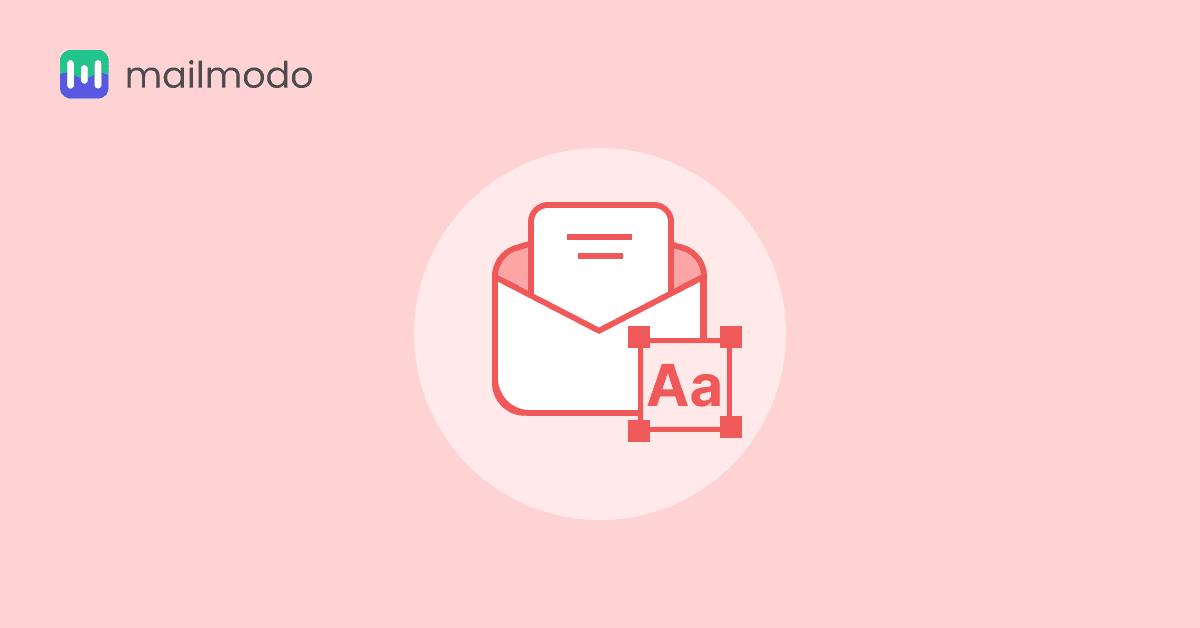
La tipografía juega un papel crucial en el éxito de tus campañas de email marketing. Una fuente bien elegida mejora la legibilidad, refuerza tu mensaje y crea una experiencia positiva para el usuario; mientras que una mala elección puede dificultar la lectura, generar confusión o incluso que tu email sea marcado como spam.
Tipos de Fuentes para Email: ¿Email-Safe vs Web-Safe?
No todas las fuentes se renderizan correctamente en todos los clientes de correo electrónico. Es fundamental comprender la diferencia entre fuentes email-safe y web-safe :
Fuentes Email-Safe
Estas fuentes están preinstaladas en la mayoría de los dispositivos y garantizan una visualización consistente en la gran mayoría de los clientes de correo electrónico, como Gmail, Outlook y Apple Mail. Ejemplos:
- Arial
- Times New Roman
- Georgia
- Verdana
- Courier New
- Lucida Sans
- Trebuchet MS
Fuentes Web-Safe
Estas fuentes están instaladas en la mayoría de los sistemas operativos, pero existe una mayor probabilidad de que no se rendericen correctamente si el dispositivo del receptor no las admite. Ejemplos:
- Helvetica
- Trebuchet MS
- Comic Sans MS
- Palatino Linotype
- Impact
- Lucida Console
- Lucida Grande
- Calibri
- Constantia
- Corbel
- Arial Narrow
- Terminal
- Century Gothic
- Papyrus
- Book Antiqua
- Cambria
- Candara
- Consolas
- Arial Black
- Arial MT Condensed Light
- Franklin Gothic Medium
- French Script MT
- Segoe UI
- Segoe Print
- Sylfaen
| Aspecto | Fuentes Email-Safe | Fuentes Web-Safe |
|---|---|---|
| Compatibilidad | Totalmente compatibles con la mayoría de los clientes de correo electrónico. | Principalmente compatibles con navegadores web, pero pueden no serlo con clientes de correo electrónico. |
| Uso | Ideales para email marketing y correos electrónicos transaccionales. | Mejores para sitios web o contenido online donde se requiere una visualización consistente en los navegadores. |
| Fuente de reserva | Incluyen una fuente de reserva para asegurar la legibilidad. | Pueden necesitar fuentes de reserva genéricas (p. ej., sans-serif o serif). |
| Personalización | Personalización limitada. | Mayor flexibilidad para los diseñadores. |
Recomendación: Prioriza las fuentes email-safe para asegurar la compatibilidad y la legibilidad en todos los clientes.
Cómo Elegir la Mejor Fuente para tu Email
La elección de la fuente debe considerar varios factores:
Considera el tono y la estructura de la fuente:
La psicología de las fuentes es importante. Una fuente moderna como Roboto o Verdana es adecuada para un público joven, mientras que una fuente serif como Times New Roman puede resultar más formal y profesional.
Tipos de familias de fuentes:
- Serif: Con serifas (pequeñas líneas al final de los trazos). Aspecto tradicional y formal (ej. Times New Roman, Georgia).
- Sans Serif: Sin serifas. Aspecto limpio y moderno (ej. Arial, Helvetica, Verdana).
- Decorativas: Estilos variados, alta expresividad, menor legibilidad (ej. Comic Sans, script).
Legibilidad y accesibilidad:
Prioriza la simplicidad y la claridad. Evita fuentes intrincadas que dificulten la lectura, especialmente para usuarios con discapacidades visuales. Fuentes como Arial y Verdana son excelentes opciones para la legibilidad.
Tamaño de la fuente:
Un tamaño de fuente demasiado pequeño dificulta la lectura, mientras que uno demasiado grande puede resultar abrumador. Se recomienda un tamaño de 14-16 px para el cuerpo del texto y 18-20 px para los encabezados.
7 Fuentes Recomendadas para Email Marketing
Analicemos algunas de las mejores opciones:
Arial:
Tipo: Sans serif. Tono: Moderno y legible. Uso: Cuerpo del texto.
Times New Roman:
Tipo: Serif. Tono: Formal y profesional. Uso: Cuerpo del texto o párrafos largos.
Georgia:
Tipo: Serif. Tono: Elegante y clásica. Uso: Newsletters y contenido extenso.
Helvetica:
Tipo: Sans serif. Tono: Neutro y moderno. Uso: Encabezados y elementos visuales.
Verdana:
Tipo: Sans serif. Tono: Amigable y simple. Uso: Encabezados, elementos visuales y contenido extenso.
Lucida Sans:
Tipo: Sans serif. Tono: Clara y amigable. Uso: Textos diversos, tablas, formularios.
Trebuchet MS:
Tipo: Sans serif. Tono: Moderno e informal. Uso: Textos del cuerpo, encabezados, subtítulos y CTA.
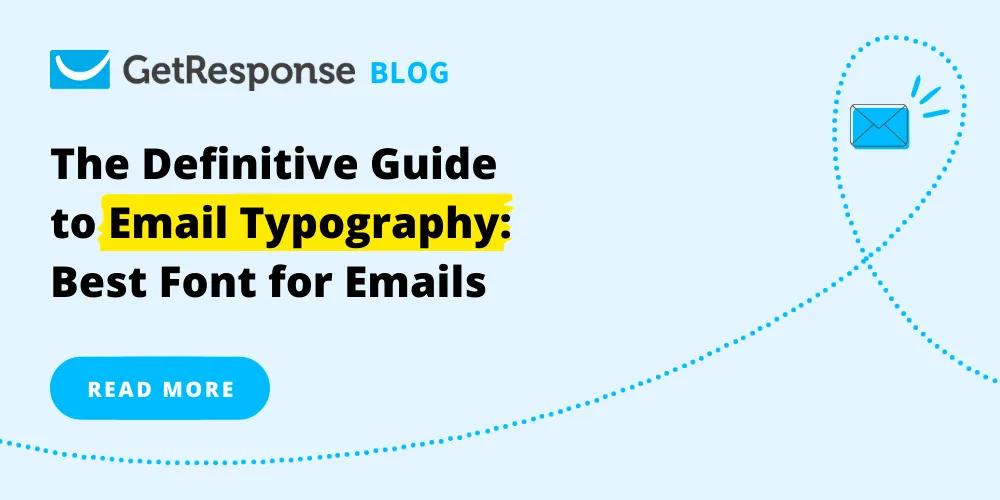
¿Qué pasa si mi fuente web-safe no se renderiza?
Aunque las fuentes web-safe están diseñadas para ser compatibles, siempre existe la posibilidad de que no se rendericen correctamente. En ese caso, la mayoría de las plataformas de correo electrónico utilizan una fuente de reserva para asegurar la legibilidad.
Uso de Fuentes Estéticas en Imágenes
Para usar fuentes más estéticas sin comprometer la compatibilidad, puedes incrustarlas en imágenes. Sin embargo, recuerda que el uso excesivo de imágenes puede aumentar el tamaño del correo electrónico y afectar su entrega.
Pruebas A/B para la Optimización
Realiza pruebas A/B con diferentes fuentes para determinar cuál funciona mejor para tu público objetivo y tus objetivos de marketing.
Recuerda que la elección de la fuente es un elemento crucial de tu estrategia de email marketing. Experimenta, analiza los resultados y optimiza tus campañas para lograr el máximo impacto.